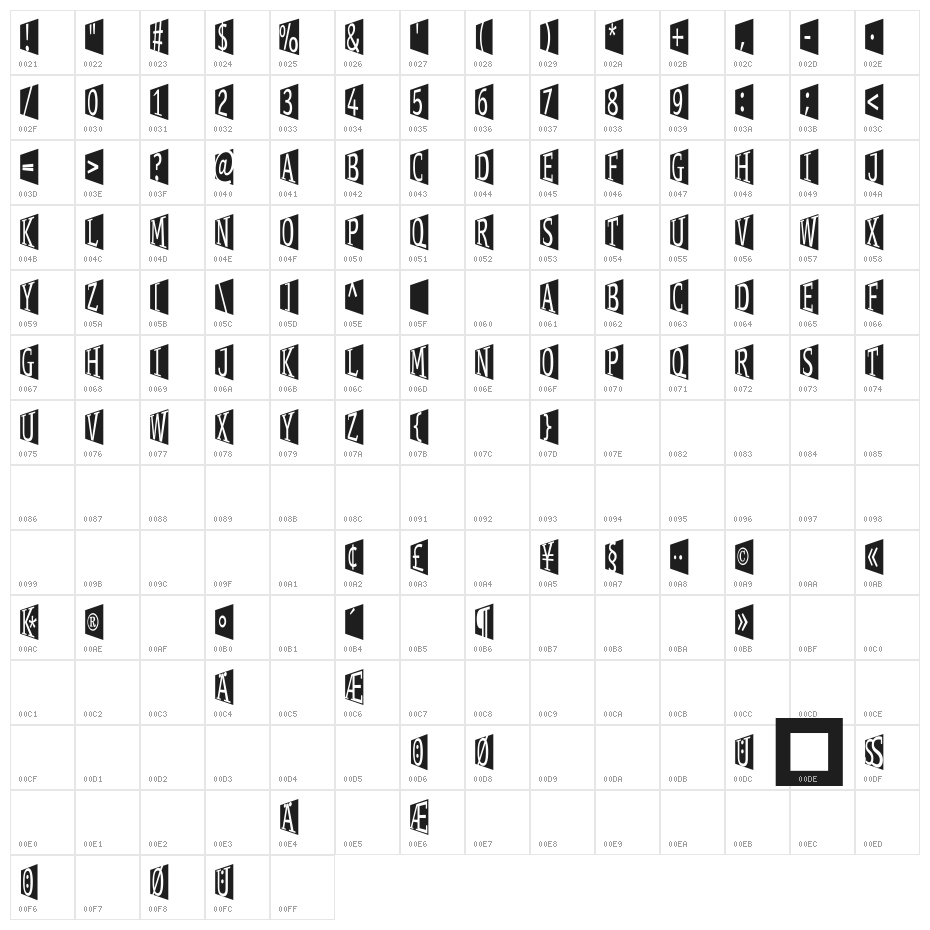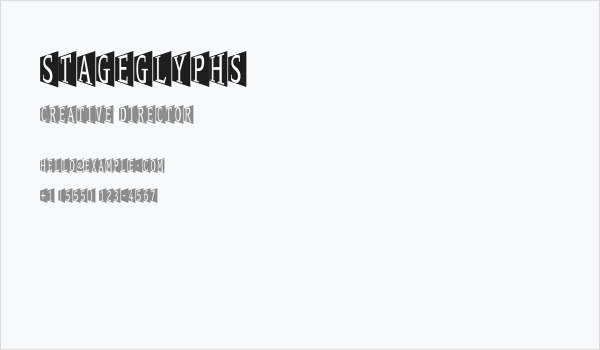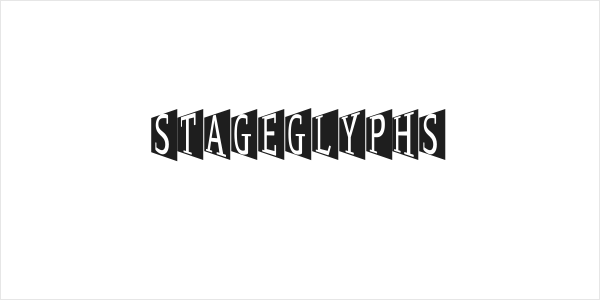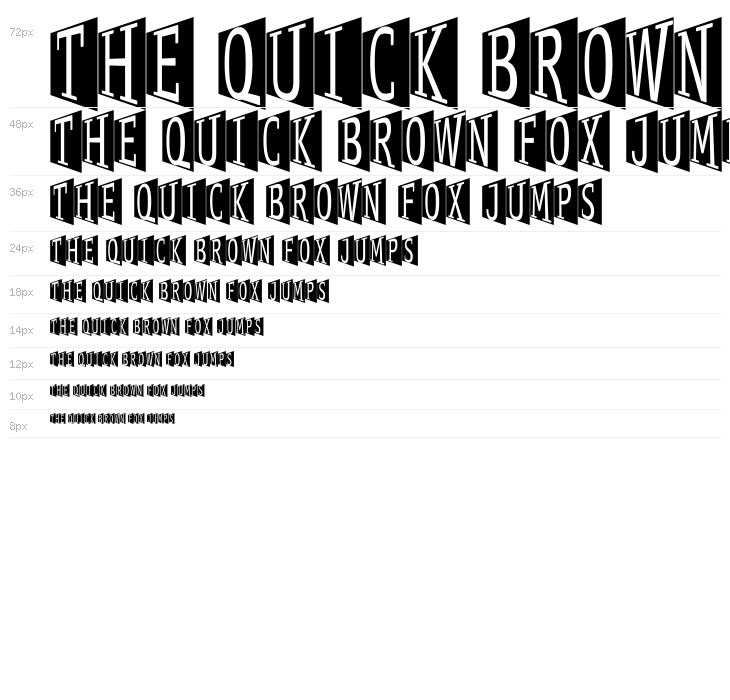
StageGlyphs Font
| Proyectos propuestos | Ideal for posters, signage, theatrical productions, and any project requiring a dramatic and eye-catching typeface. |